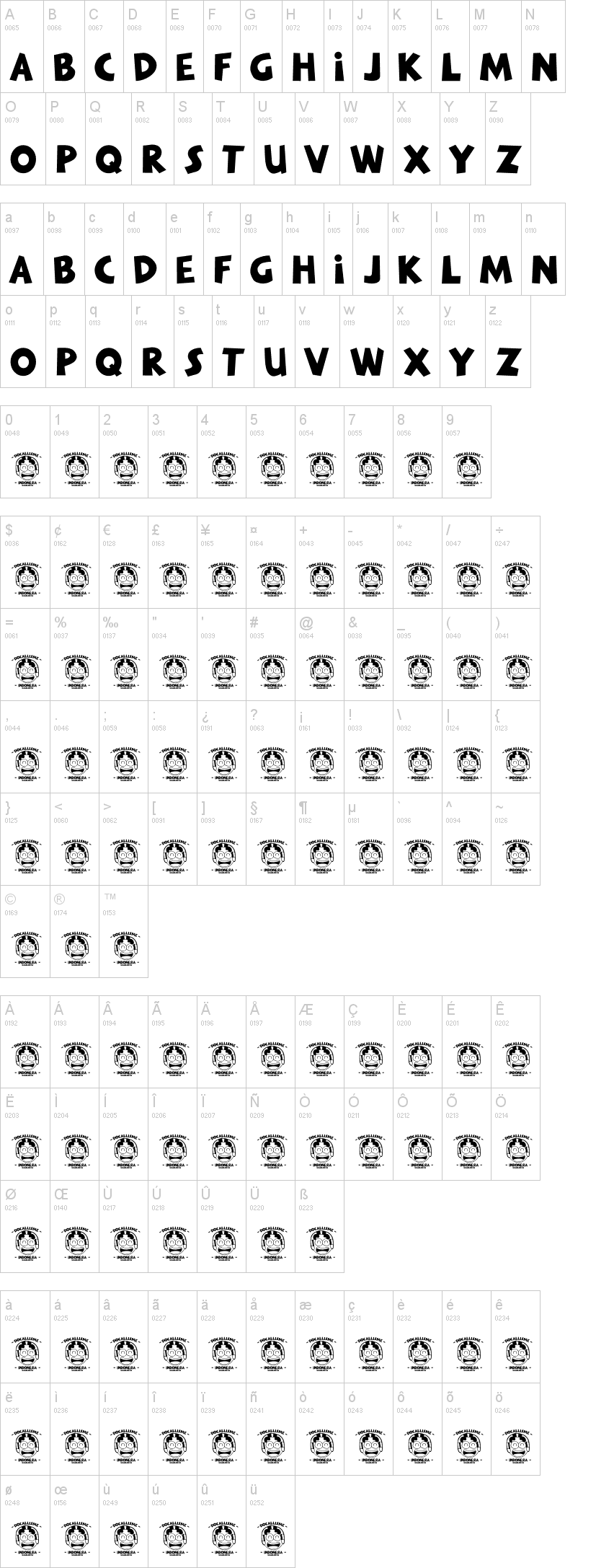
Glory United 字体是一款由字体工作室 Fontfabric 创作的高质量英文字体,它结合了抽象线条和柔和的曲线,形成了一种有力的复古风格。这款字体有 10 个字重,包括细体、常规体、中等体、粗体、黑体等,每一种字重都有丰富的符号和标点符号,可以满足您的任何设计需求。Glory United 字体能够支持多种语言,支持多种操作系统,并且拥有极佳的可读性和可视性,是一款非常适合用于商业广告、报纸、杂志、网站等设计的字体。内容介绍
Glory United是一款非常不错的手写艺术字体,具有很好的视觉感,适合于文化类的宣传设计、商业类品牌的广告和产品包装设计以及个性化文字排版等较多场景。